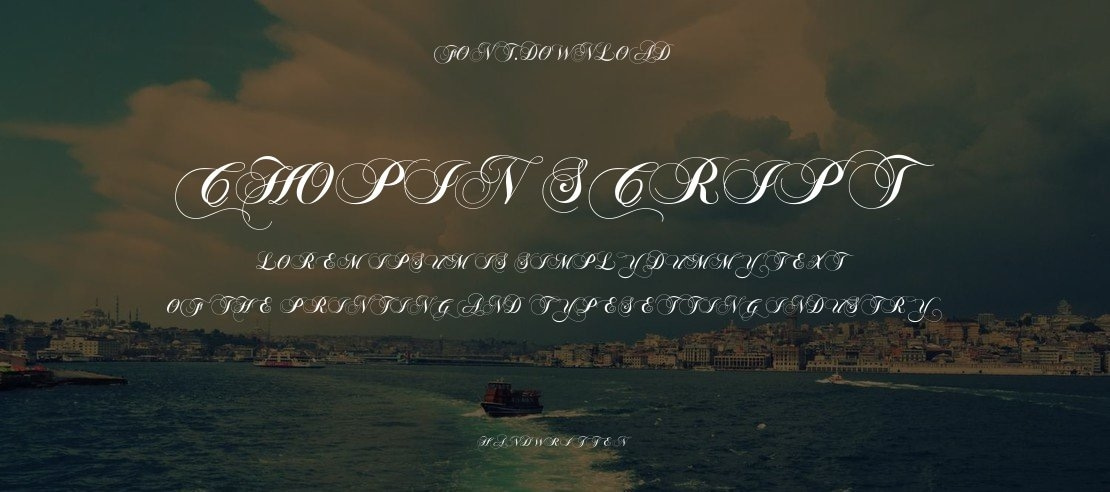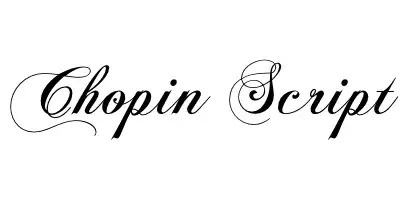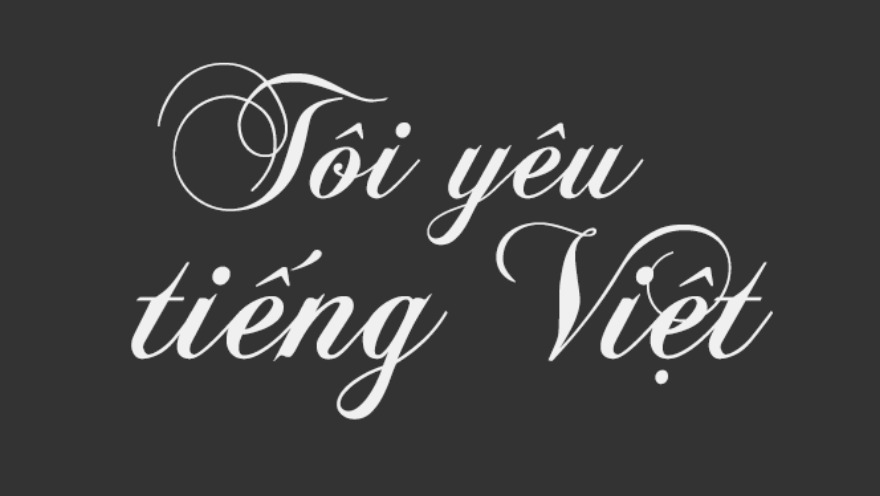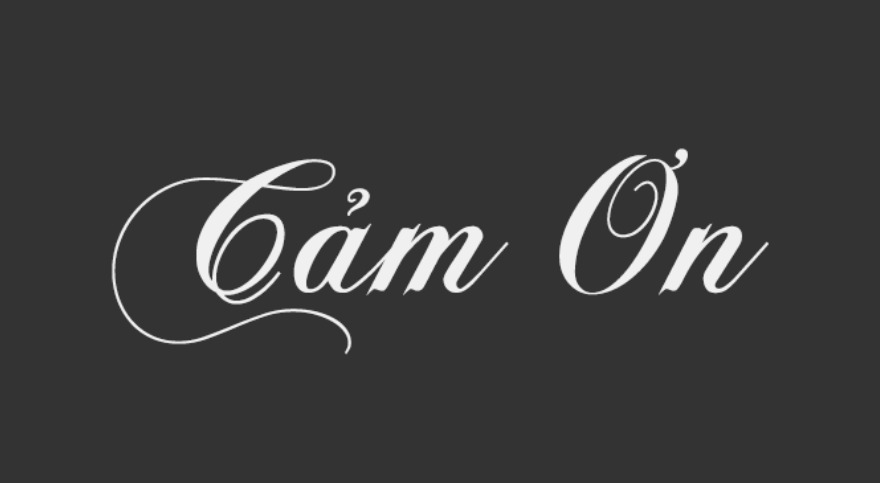
Font UVF Chopin Script là bộ phông chữ thuộc dòng Calligraphy Script cổ điển mang phong cách thư pháp quý tộc châu Âu thế kỷ 18, nổi bật với những đường nét uốn lượn lộng lẫy, thanh thoát và đậm chất âm nhạc cổ điển. Được lấy cảm hứng từ nghệ thuật thư pháp bút lông kim loại Copperplate và được đội ngũ UVF tinh chỉnh hoàn chỉnh hệ thống dấu tiếng Việt, Chopin Script là lựa chọn hoàn mỹ cho các thiết kế thiệp cưới hoàng gia, nhãn chai rượu vang lâu năm và hộp quà tặng cao cấp. Doozypack.vn chia sẻ link download font UVF Chopin Script chuẩn kỹ thuật, giúp bạn sở hữu phông chữ quý phái mà không gặp bất kỳ lỗi hiển thị dấu thanh nào khi thiết kế in ấn.
Đặc điểm thẩm mỹ độc đáo của Font UVF Chopin Script
Chopin Script tái hiện trọn vẹn sự tinh tế và tráng lệ của các bức thư tay quý tộc thời kỳ Baroque, nơi mỗi nét chữ đều mang nhịp điệu của một bản giao hưởng êm dịu.
Vũ điệu thư pháp cổ điển lấy cảm hứng từ âm nhạc Chopin
Đặc trưng lớn nhất của Font UVF Chopin Script là sự tương phản cực đại giữa các nét nhấn đậm đà và các nét đưa bút thanh mảnh như sợi tóc (hairline). Cấu trúc chữ có độ nghiêng chuẩn mực theo phong cách Italic cổ điển, các đường nét liên kết nhịp nhàng tạo nên một dòng chảy văn bản trôi chảy, quý phái. Khi sử dụng phông chữ này làm tiêu đề trên bao bì, thương hiệu của bạn sẽ ngay lập tức toát lên vẻ trang trọng, đẳng cấp và mang chiều sâu di sản văn hóa lâu đời.
Đường nét thanh đậm sắc sảo với các nét uốn quý phái
Các ký tự hoa của Chopin Script sở hữu những đường xoắn ốc (swashes) và nét lượn sóng cầu kỳ, biến mỗi chữ cái đầu dòng thành một tác phẩm nghệ thuật đồ họa độc bản. Nhờ đó, phông chữ này mang lại diện mạo kiêu kỳ, lộng lẫy cho các ấn phẩm kỷ niệm, giấy chứng nhận hoặc các dòng sản phẩm quà tặng sang trọng.
03 Ưu điểm nổi bật của bản font UVF Chopin Script Việt hóa
Khi ứng dụng các phông chữ thư pháp cổ điển vào thị trường trong nước, sự chỉn chu về dấu câu là yếu tố quyết định đến tính chuyên nghiệp của bản thiết kế:
- Khắc phục triệt để lỗi dấu tiếng Việt: Phiên bản Việt hóa của Chopin Script đã được trau chuốt thủ công từng dấu câu. Các dấu sắc, huyền, hỏi, ngã, nặng được vẽ thanh mảnh, uốn lượn mềm mại theo thân chữ, không gây cảm giác chắp vá hay va chạm vào các đường nét hoa mỹ xung quanh.
- Bảo đảm tính đồng nhất thương hiệu: Việc tải font UVF Chopin Script chuẩn giúp bạn tự tin dàn trang tiêu đề tiếng Việt mà không lo hiện tượng lỗi ô vuông hay nhảy về font hệ thống khô khan.
03 Ứng dụng thực tế của font UVF Chopin Script trong sản xuất bao bì
Sự quý phái và lộng lẫy của Chopin Script mang lại hiệu ứng thị giác đắt giá trên các dòng sản phẩm bao bì thực tế do Doozypack.vn sản xuất:
- Hộp giấy đựng Nước hoa & Mỹ phẩm Luxury: Tiêu đề thương hiệu in bằng nét chữ Chopin Script kết hợp kỹ thuật ép kim nhũ vàng trên giấy Ivory cán màng mờ tạo nên vẻ đẹp sang trọng chuẩn phong cách hoàng gia.
- Thiệp cưới & Thiệp cảm ơn cao cấp: Nét chữ viết tay uốn lượn duyên dáng là lựa chọn hoàn mỹ cho những lá thư tri ân đính kèm hộp quà, giúp gia tăng thiện cảm và sự gắn kết với khách hàng.
- Nhãn dán chai Rượu vang lâu năm: Nét chữ thư pháp cổ điển mang lại cảm giác truyền thống, uy tín và khẳng định phẩm cấp thượng hạng của sản phẩm.
Lưu ý kỹ thuật khi in ấn với phông chữ thư pháp thanh mảnh Chopin Script
Việc sản xuất bao bì thực tế sử dụng các phông chữ có đường nét thanh mảnh như Chopin Script đòi hỏi sự am hiểu kỹ thuật chuyên sâu tại xưởng in Doozypack.vn:
- Kiểm soát độ dày nét Hairline khi ép kim: Các nét vuốt mảnh của font chữ này rất mỏng. Khi gia công ép kim vàng (Hot Stamping), designer nên đảm bảo nét chữ có độ dày tối thiểu 0.15mm để nhũ bám dính sắc nét, không bị đứt đoạn.
- Chọn chất liệu giấy phẳng mịn: Chopin Script đẹp nhất khi in trên giấy Ivory, Couche hoặc giấy mỹ thuật nhẵn. Tránh in các nét chữ quá thanh trên bề mặt giấy Kraft thô nhám vì mực dễ bị loang làm mất đi độ sắc sảo của nét chữ.